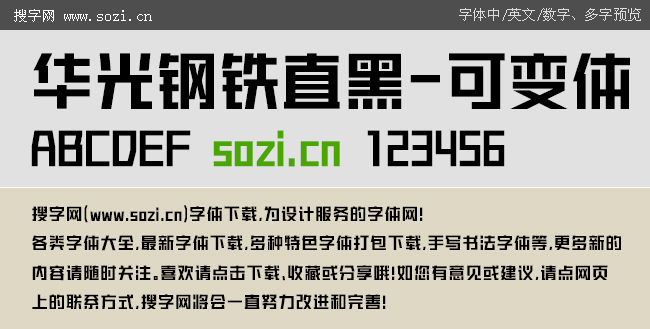
華光鋼鐵直黑-可變體
搜字網(wǎng)給大家提供一款華光鋼鐵直黑-可變體中文字體下載,華光鋼鐵直黑是一款藝術(shù)黑體字體。字體筆畫平直,線條規(guī)整,結(jié)構(gòu)扎實,字形方正,視覺效果非常不錯 。免費供大家使用。適合應(yīng)用于藝術(shù)設(shè)計、平面宣傳設(shè)計、網(wǎng)頁設(shè)計、海報設(shè)計等應(yīng)用。
- 風格類別: 現(xiàn)代藝術(shù)體